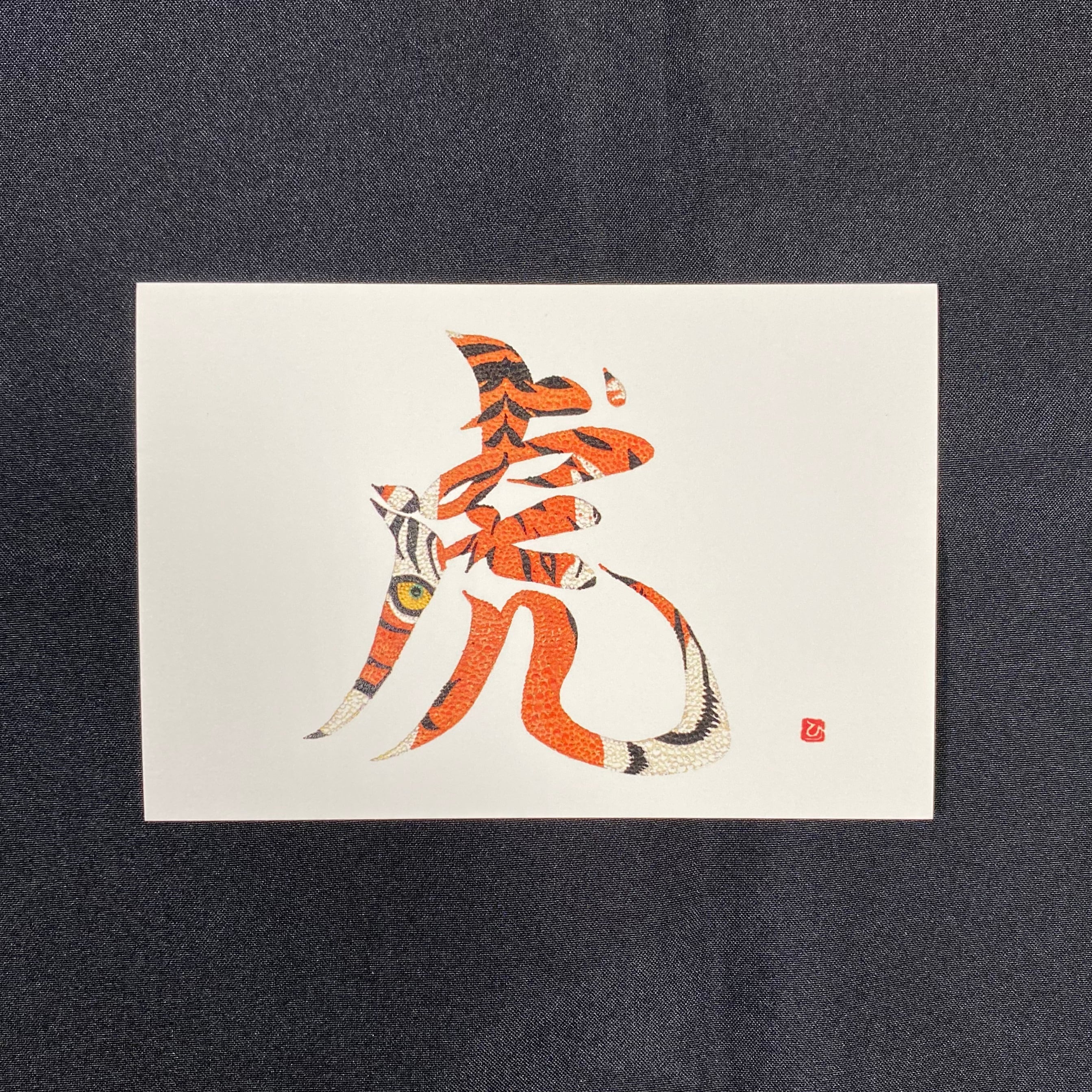
虎~おうえん~(虎カラー)はがきサイズ
【虎】
虎という作品ですが、よく見るとひらがなの「おうえん」で作られた
「虎」のこころMojiになっています。
原画はA5サイズ・水彩・点描画。
『虎』~おうえん~
寅年生まれの人は前向きでチャレンジ精神が強く、
どんなことにも強い信念を持って挑んでいく傾向が
あります。たとえ失敗したとしても、めげずに何度も
立ち向かっていく姿は、多くの人に好意を持たれ、
周囲の人を味方にします。